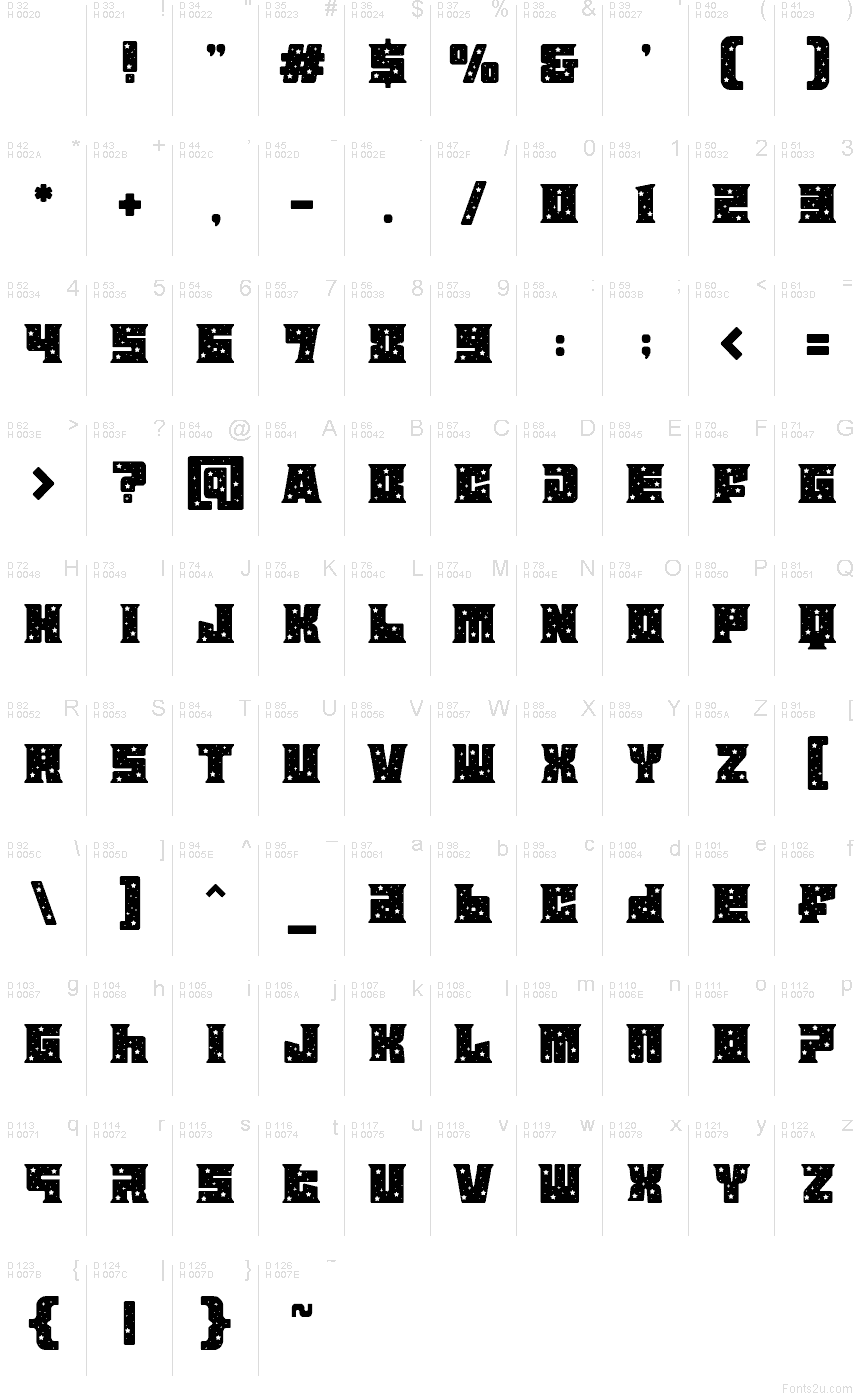
Astral Zenith Eight od Putracetol Studio je bezplatné písmo s vesmírnou tematikou, které mění bloková písmena v pole vyřezávaných hvězd. Opakující se pěticípé hvězdy a drobné jiskry jsou rozprostřeny v každém znaku, takže design nepůsobí jako prostá dekorace, ale spíše jako textura noční oblohy vyrytá do pevné siluety.
Díky tomuto zpracování je písmo ideální volbou pro sci-fi plakáty, pozvánky na kosmické večírky, bannery streamerů, dětské vesmírné projekty i tematické dárkové předměty, kde musí litery nést téma samy o sobě. Krátké nadpisy a titulky typu loga z něj těží nejvíce, protože hustý hvězdný vzor dodává velkým slovům výrazný grafický povrch.
Astral Zenith Eight